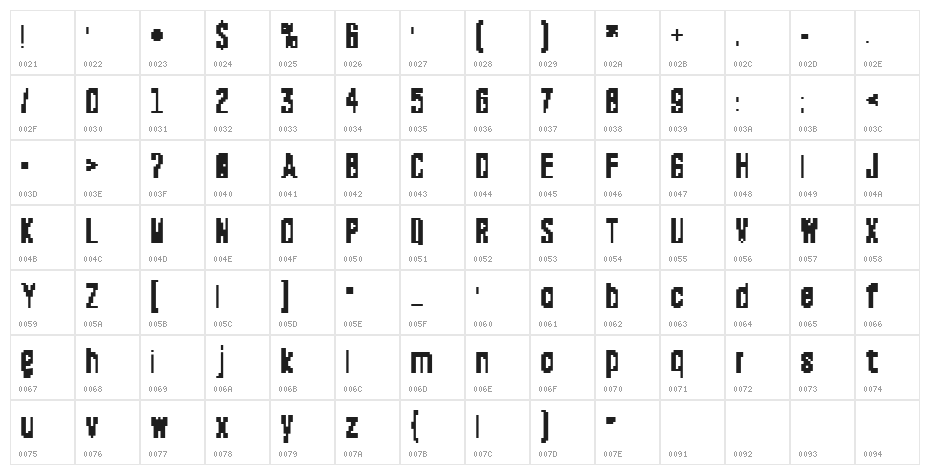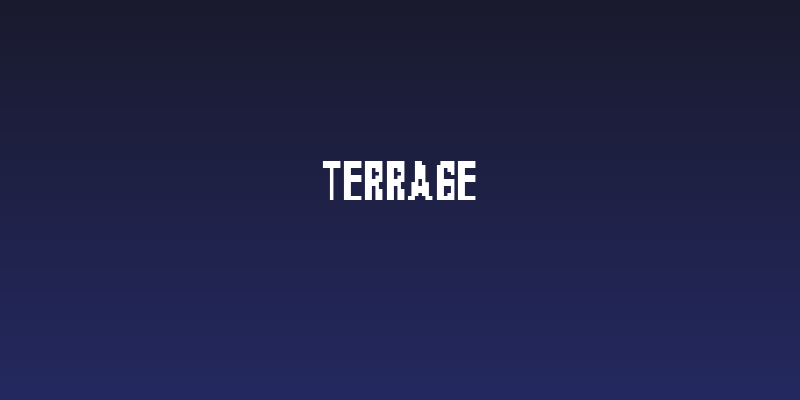
Terrage Font
✎ Futuristic
| Kategorien | Futuristic |
| Gesamtstil | Retro, Digital |
| Vorgeschlagene Projekte | Ideal for projects that require a retro or digital aesthetic, such as video game graphics, tech-themed posters, or nostalgic branding materials. |